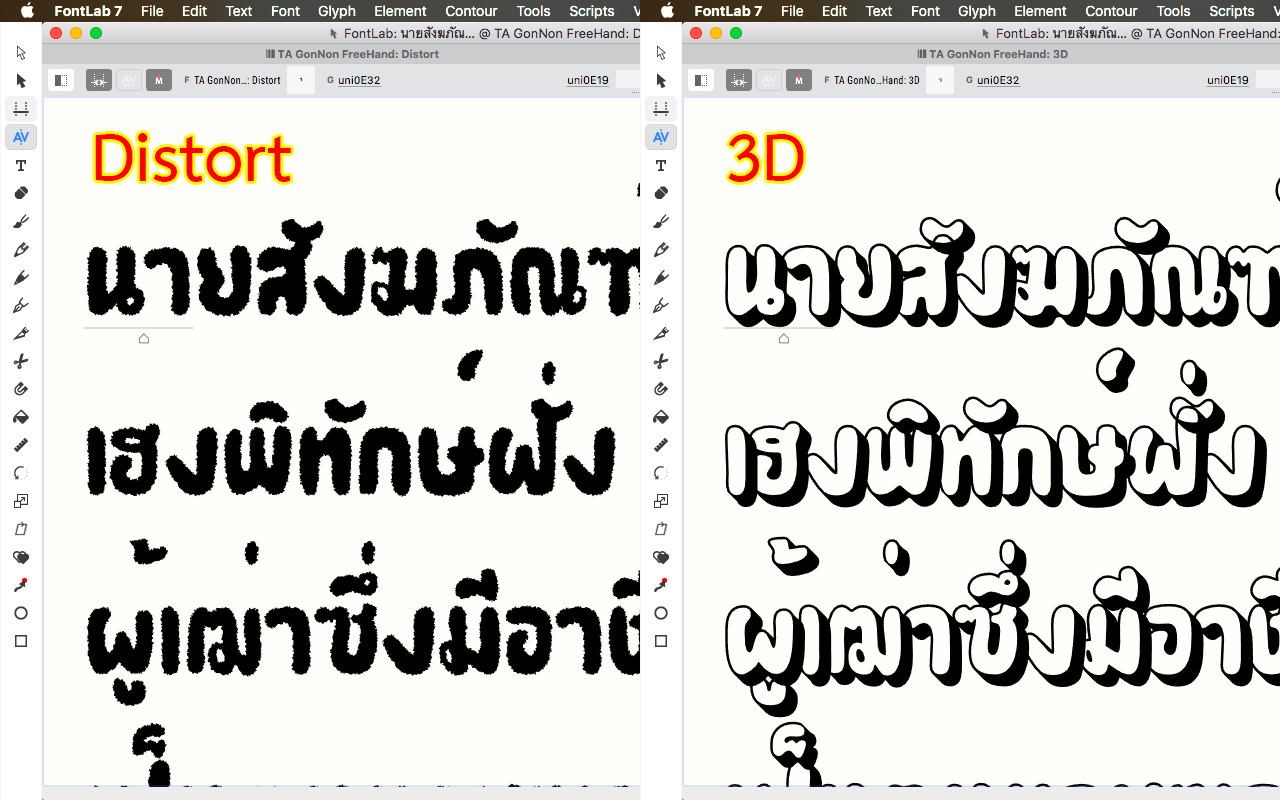
Fontlab-วิธีทำ เงา,3D ฯลฯ อย่างง่ายและเร็ว
กระทู้นี้จะมาแนะนำวิธีเพิ่มลูกเล่นให้ฟ้อนต์ของเรา
อย่างง่ายและเร็วด้วยโปรแกรม Fontlab 7 นะครับ
หลักๆ จะแนะนำวิธีทำเงา(Shadow)ให้กับฟ้อนต์นะ  :27:
ซึ่งจะใช้ Action ที่โปรแกรม FL7 มีมาให้ในการแปลงฟ้อนต์เดิมของเราเป็น Shadows Font ครับ
เทคนิคเดียวกันนี้สามารถทำฟ้อนต์ไสต์อื่นๆ ได้อีกนะ เพราะโปรแกรม FL7 มีแอคชั่นให้เล่นหลายอันอยู่
อย่างเช่น ทำ 3D ,ทำขอบแตกให้ฟ้อนต์(Distort), ทำ Texture ให้ฟ้อนต์
หรือใช้ทำตัวเอียง รวมไปถึง perpective ให้ฟ้อนต์ก็ทำได้เช่นกัน
เทคนิคนี้ พี่ปอมป๋วยเคยแนะนำไว้บ้างแล้ว ผมจะเขียน Step By Step ตามที่ผมเข้าใจนะครับ
ในที่นี้ขอเอาฟ้อนต์ ทีเอ ก่อนนอน มาเป็นตัวอย่างนะครับ
ตอนเอาฟ้อนต์นี้มาแจกลืมทำตัวเอียงด้วย
ฟ้อนต์ตัวนี้เดิมผมทำไว้ 2 น้ำหนัก คือ 1.ตัวปกติ (มีไฮไลท์) 2.ตัวหนา (ทึบ ไม่มีไฮไลท์)
เริ่มแรก ก่อนที่จะเริ่มทำเงาให้ฟ้อนต์ ผมจะทำการคัดลอกฟ้อนต์ก่อนนอน ตัวหนา(ทึบ) ขึ้นมาอีก 1 ชุด(1 น้ำหนัก) ก่อนนะครับ ซึ่งวิธี คือ...
1.คลิกที่ปุ่ม ตัว 'i'(info) จะมี เมนู Font Info ขึ้นมา
2.คลิกเลือก '+' แล้ว > เลือก คลิกเลือก Copy font ...ชื่อฟ้อนต์... > คลิกเลือก Bold (สไตล์ฟ้อนต์ที่ต้องการคัดลอก)
3.ตั้งชื่อรูปแบบของฟ้อนต์ที่จะทำให้ครบถ้วน
*(เนื่องจากไม่ใช่สไตล์ปกติทั่วไปโปรแกรมจะไม่ตั้งให้อัตโนมัติ กดที่เพชรไม่ได้เด้อ)
4.จะได้ฟ้อนต์ที่เรา copy เพิ่มมาอีก 1 ชุด
5.กดปุ่ม "Ctrl+A' เลือก Glyph ทั้งหมด
6.คลิกเลือก Tool > คลิกเลือก Action
7. ทำตามขั้นตอนในภาพเลย ซึ่งในแถบแอคชั่นจะมีคำสั่งสำเร็จรูปอีกหลายตัวให้ใช้
ลองๆ เล่นกันดู -- ถ้าใครจะทำตัวเอียงก็ทำจากตรงนี้ได้เช่นกัน
8. ตั้งค่าเสร็จก็กด Run >> กด OK
เสร็จแล้ว!!!
ที่เหลือก็ตรวจสอบ เก็บรายละเอียด ดูครับ
เพราะบางทีผลลัพธ์อาจผิดเพี้ยนได้
ลองทำแบบ Distort , 3D ดูบ้าง
ลองๆ เอาไปทำกันดูครับ สนุกๆ แนะนำไว้เผื่อมือใหม่ หรือบางคนยังไม่รู้
เผื่อจะช่วยให้มีฟ้อนต์หลายๆ แบบไว้ใช้งานได้อีกครับ
*ตอนที่ผมทำฟ้อนต์ทีเอก่อนนอน ตอนนั้นผมนำฟ้อนต์มาจากเว็บ Caligraph.com (แปลงลายมือเป็นฟ้อนต์)
จะมี Node แปลกๆ ซ้อนกันเยอะมาก ผมก็ใช้ Action ของโปรแกรมนี้
ช่วย clean ,ช่วยปรับ smoot ทำให้ประหยัดเวลา ช่วยให้ทำงานง่ายขึ้นเยอะเลย
มาทำ layer font กัน  :43: